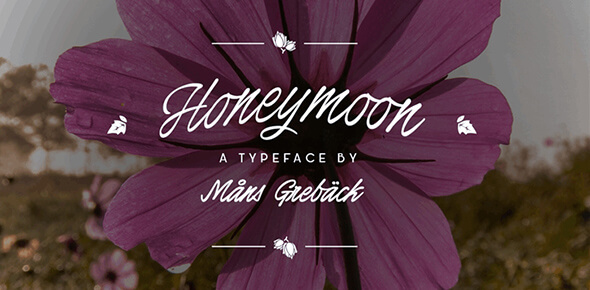
ポスターイラストに!無料だけどエレガントなデザインの細字スタイルフォント20選!
エレガントなデザインを叶える無料の細字フォントをお探しのあなた!必見です!軽やかタッチのデザインで、モダン調からレトロ調に至るまで、様々な種類のプロジェクトに美しく映えることでしょう。
細字フォントは、結婚式招待状やポスター、カード、イラスト、ロゴなどに多様なシーンで美しく活用できます。
Respective Font(レスペクティブ・フォント)
MånsGrebäckによって考案されたすばらしいフォントです。私的利用には無償使用が認可されています。ライセンスを合わせて購入することで、商用プロジェクトにも使用可能です。
Airways フォント
この美しい書体は間違いなく人の目を引くことでしょう。同じくMånsGrebäckによって設計され、私的利用としては無料で利用可能です。
Trench フォント
Trenchは私的利用であれば無料でダウンロードして使用することができます。NimaVisualによって設計されたもので、驚くほど軽ろやかなデザインが注目の的となっています。このフォントには、3つのスタイルが包含されています。
Brannboll Fetフォント
こちらもMånsGrebäck作の美しいフォントです。私的利用のためのフリーフォントですが、商用ライセンスも販売されています。
Jenthill フォント
素敵な4つのスタイルとともに様々な言語のフォントと380の絵文字が含まれます。Katsia Jazwinskaによって設計されたもので、個人利用用の無料デモ版フォントをダウンロードすることができます。
NEOTERIC FONT
ダウンロードして使用できるすばらしい細字フォントです。Herofontsにより設計され、私的には無料で使用できます。
Before The Rainフォント
MånsGrebäck考案の手書きスタイルが美しいフォントです。ダウンロードして、あなたの今のプロジェクトや今後のデザインに活用してください。私的利用は無料。商用ライセンスも購入可能です。
Precious フォント
幻想的なデザインがユニークな手書き調のフォントです。Bolt Cutter Designによって作成されたもので、個人用と商業用の両方のデザインで無料で使用することができます。
Honeymoon フォント
こちらもMånsGrebäck作の印象的なデザインのフォントです。私的利用には無償で使用可能ですが、ライセンス条項については所定のファイルをご確認ください。
Canela Bark フォント
私的利用が可能なゴージャスなイメージのフォントです。MånsGrebäckによって作成され、あなたのデザインを美しく彩ってくれますよ。
Thirsty Script Extrabold デモフォント
Yellow Design Studioによって作成された美しい細字フォントです。私的利用にはフリー開放されたフォントです。
Goldoni フォント
洗練されたデザインのフォントで、私的には無料で利用できます。商用利用のためには専用ライセンスが必要となります。
New Garden フォント
ビリー・アーゲルによって考案されたフォントです。装飾的で創造的なデザインが実現されています。私的利用には無償使用が可能な便利ツールです。
Caneletter Script フォント
様々なプロジェクトに美しく映え、驚きさえ覚える美しく細字フォントです。ライセンス条項をご確認のうえルールを守ってご利用ください。
Across the Road フォント
Milasian Thin フォント
Monument Valleyフォント
注目されること間違いなしの創造的なイメージの細字フォントです。私的利用にも商用にも、様々な用途においてダウンロードして使用することが可能です。ポスター、チラシ、など多様なデザインを美しく彩ることでしょう。
QumpellkaNo12 フォント
様々なプロジェクトにおいて使用できるすばらしいフォントです。商用および非商用の両方において、無料でダウンロードして利用できます。
Clipper Script フォント
Goatskin Brush フォント
ブラシ調のスタイルが素晴らしい細字フォントです。注目を集めること間違いないでしょう。ライセンス条項をよくご確認のうえ、ルールを守って使用してください。